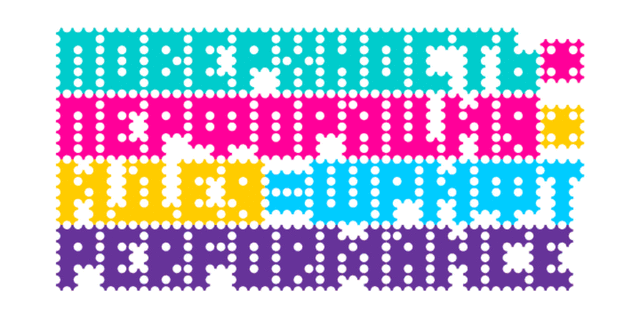
Перформанс (Performance) — это комплект перфорированных площадок, представляющих при внимательном рассмотрении знаки шрифта. Конструкция знаков определяется набором отверстий, форма и расположение которых задают характер и пластику начертаний. Одной из важных особенностей дизайна является отсутствие межбуквенных просветов и межстрочных интервалов. Благодаря этому текст, набранный Перформансом, образует связную перфорированную плоскость наподобие блока почтовых марок. Шрифт был разработан дизайнером Алексеем Боковым. Выпущен компанией ПараТайп в 2009 году.